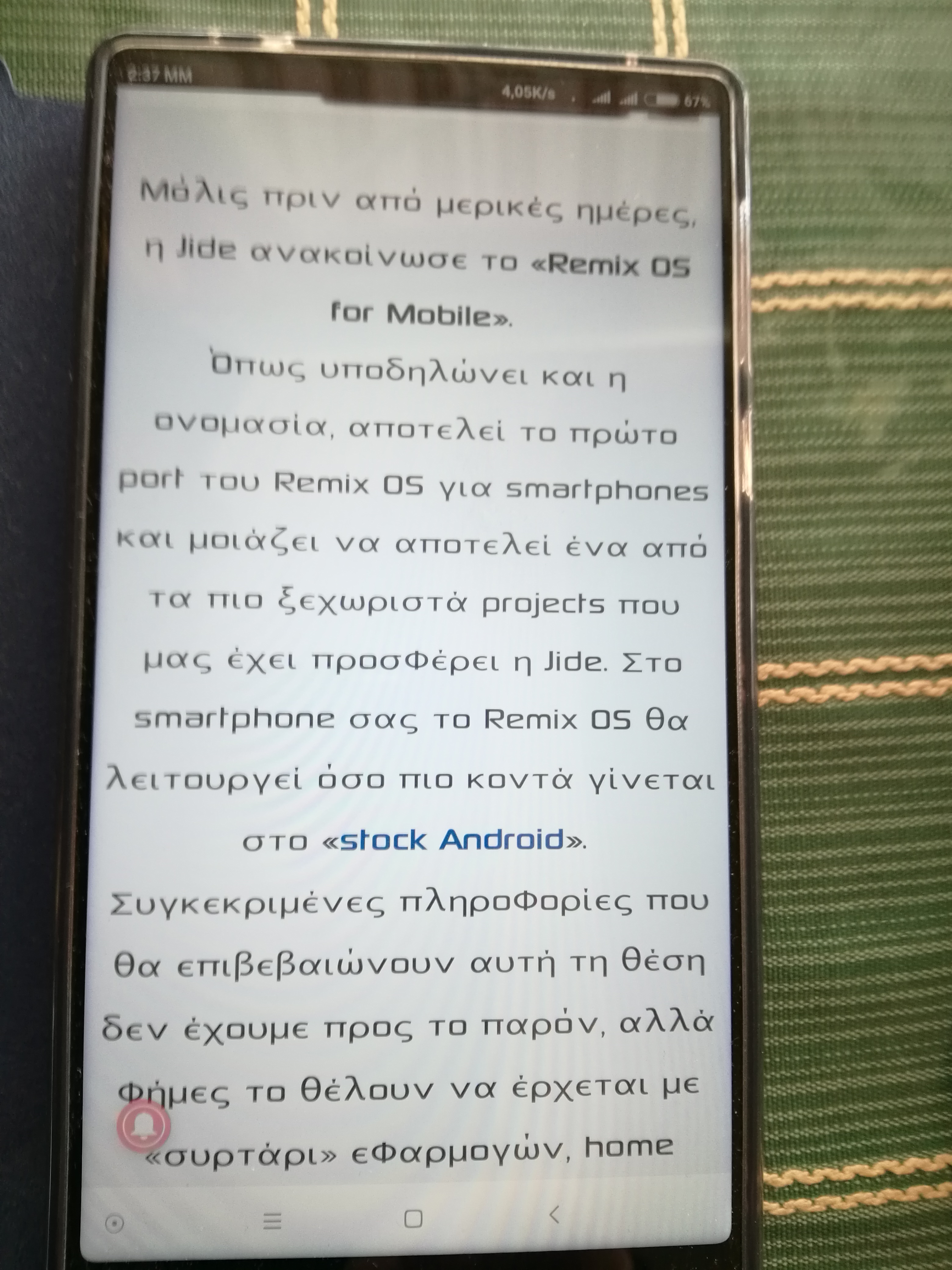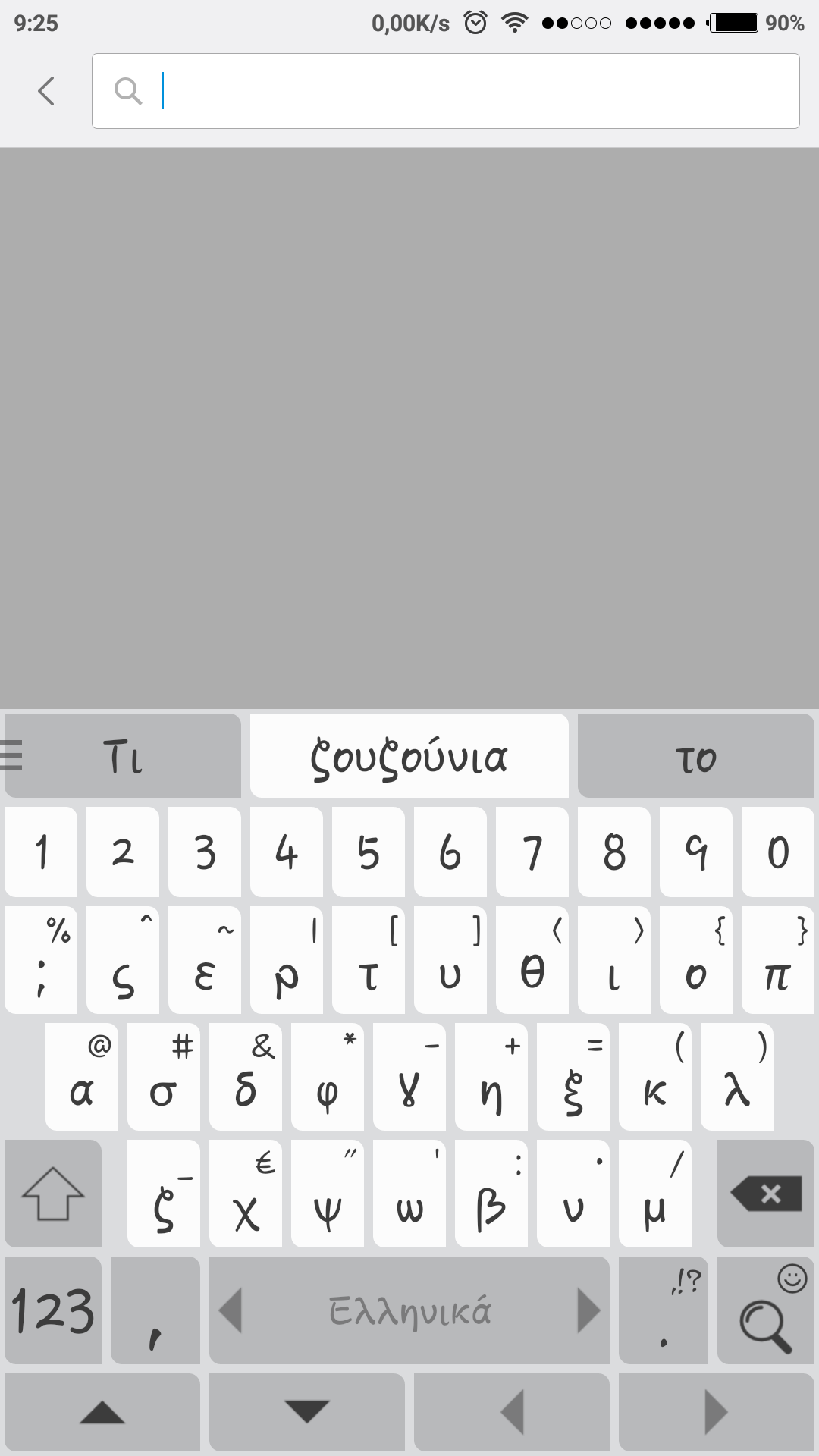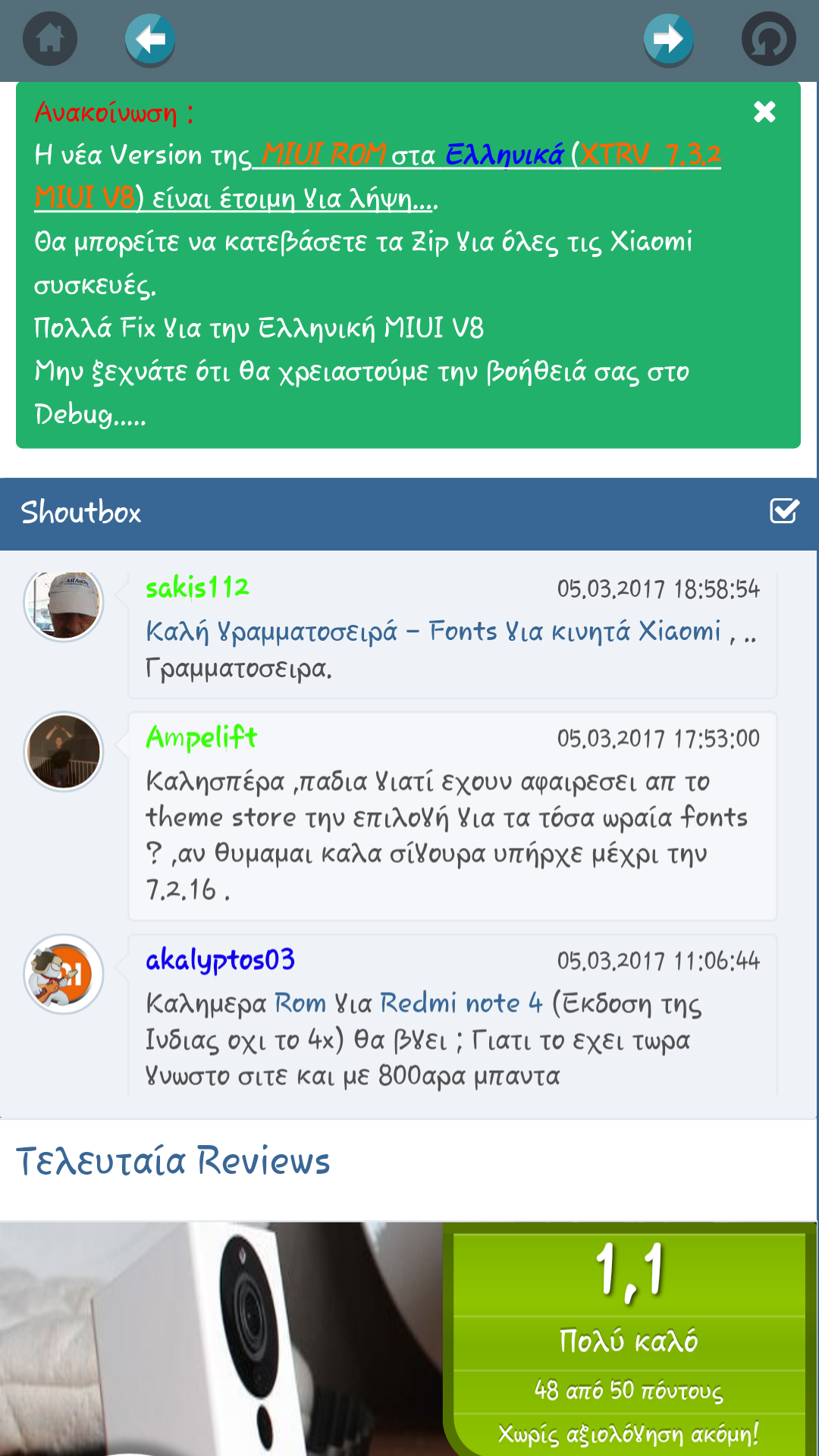
εγω το δοκιμασα πριν λιγο κατεβασα μια γραμματοσειρα chococooky και νομιζω εχει αρκετα καλα Ελληνικα το εβαλα στο MI MAX 4/128 , με stable 8.0.3.0
εγω το δοκιμασα πριν λιγο κατεβασα μια γραμματοσειρα chococook
Δοκιμασα αλλες 2 υποστηριζουν Ελληνικα αλλα δε μου αρεσαν alexander & cheeky rabbit
Η καλύτερη γραμματοσειρά που χρησιμοποιω από το miui 5 υπήρχε σε ένα θέμα με όνομα neon lamp 2.1
γραμματοσειρά.. δεν μπορω να το ανεβασω από το mi mix..
γραμματοσειρα sony sketch,, δεν μπορω να ανεβασω screenshot απο το mi mix. -
Εγω χρησιμοποιω την rosemary